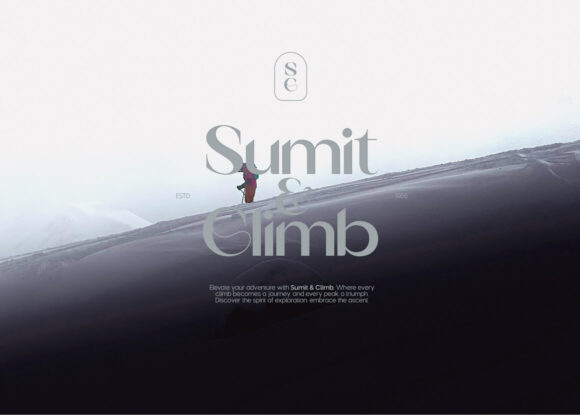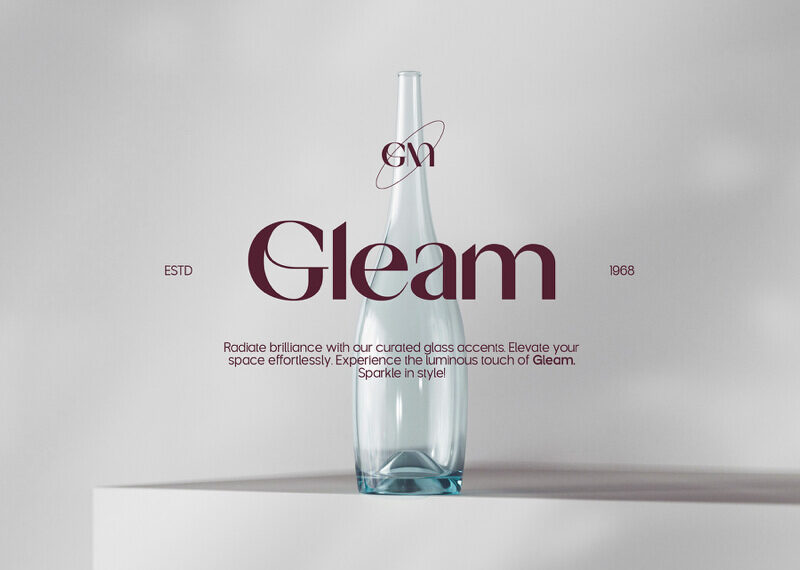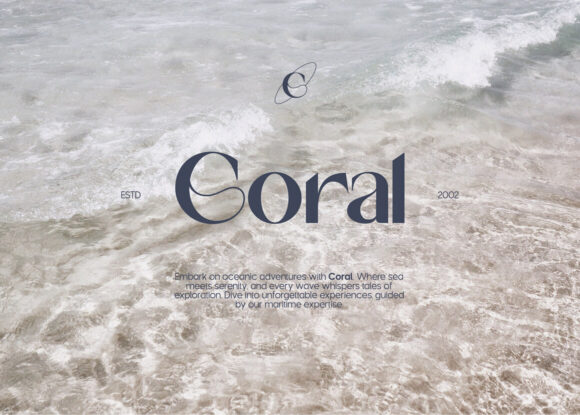
Milky: Free Modern Sans Serif Font
Milky ist eine kostenlose Sans-Serif-Schriftart, die sich durch moderne Elemente auszeichnet, die mit einem Gefühl von großer Harmonie und Eleganz kombiniert sind. Die Formen dieser Schriftart vereinen dicke Striche und feine Linien und erreichen so ein perfektes Gleichgewicht. Diese Merkmale verleihen ihr einen überwiegend femininen oder anderweitig sehr anspruchsvollen Charakter.